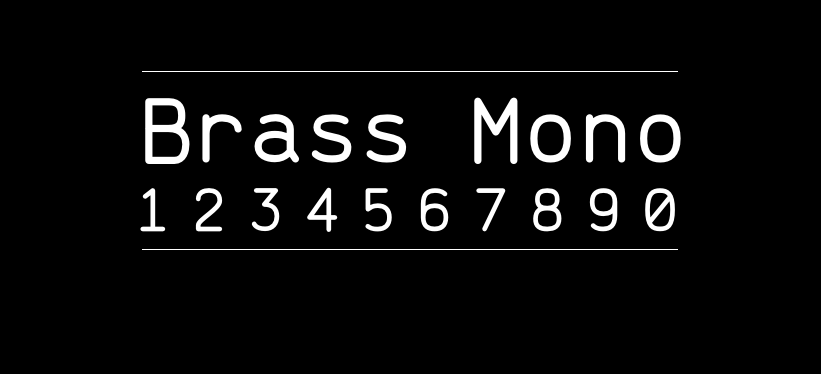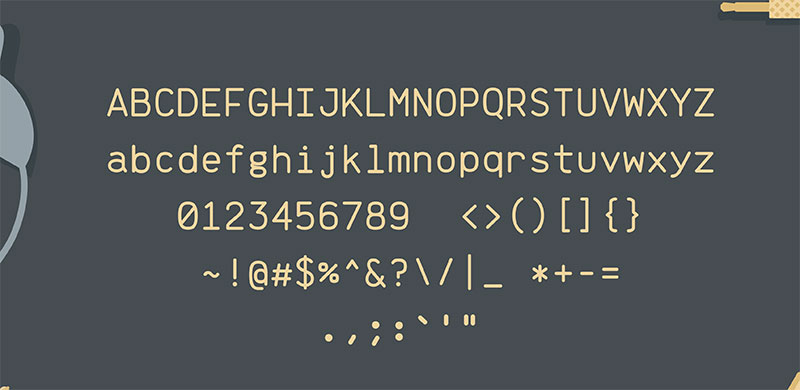
Brass Mono
Brass Mono字体介绍
一款免费的复古等宽圆角英文字体,其灵感来自70年代的电气和机械设计。该字体在Github上开源,提供了源文件供下载使用,但是未提供已导出的字体文件,自由字体将其导出,并提供打包下载。该字体提供了3种不同的字体宽度(间距)以方便大家的排版。
Brass Mono字体应用示例